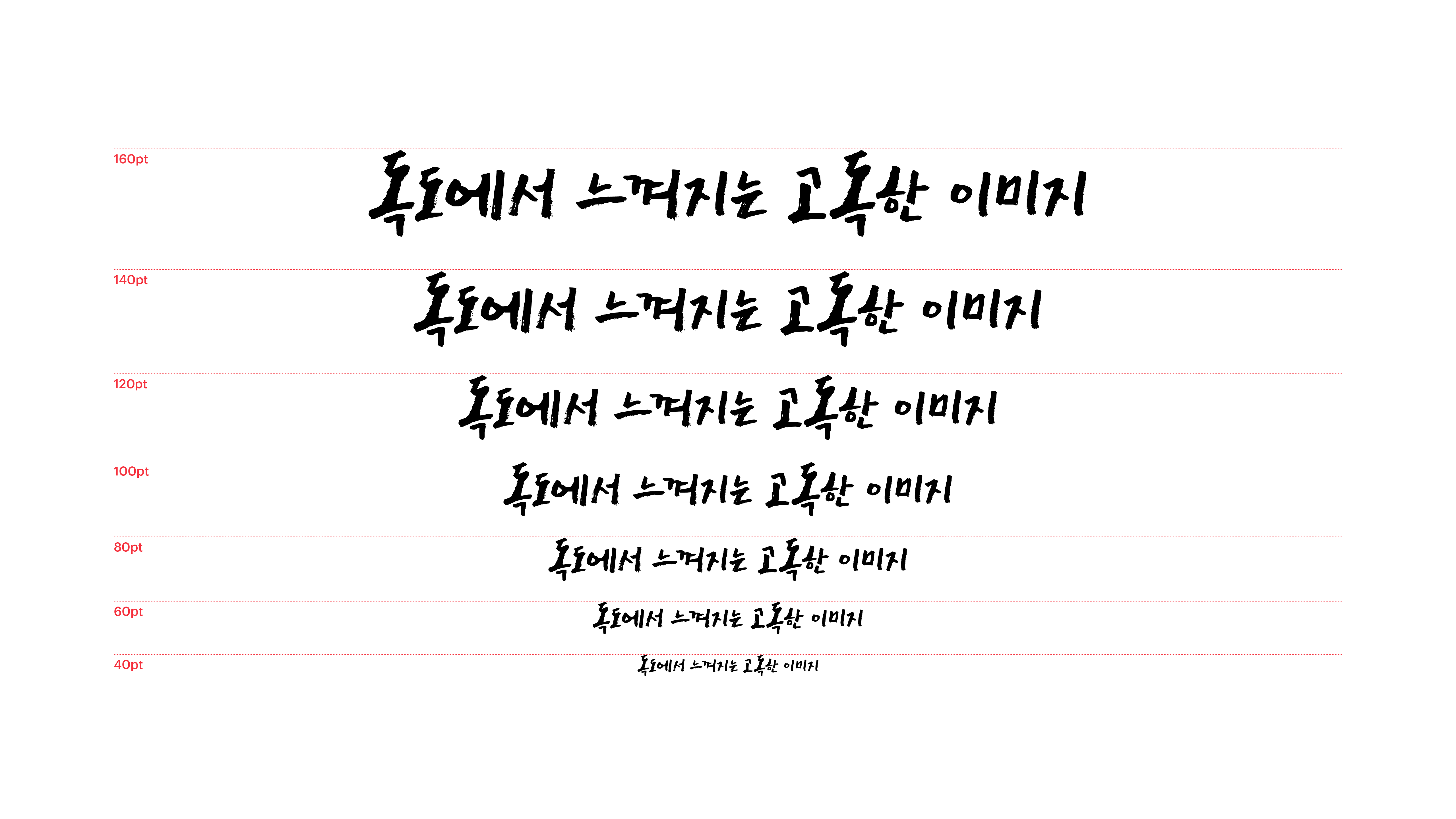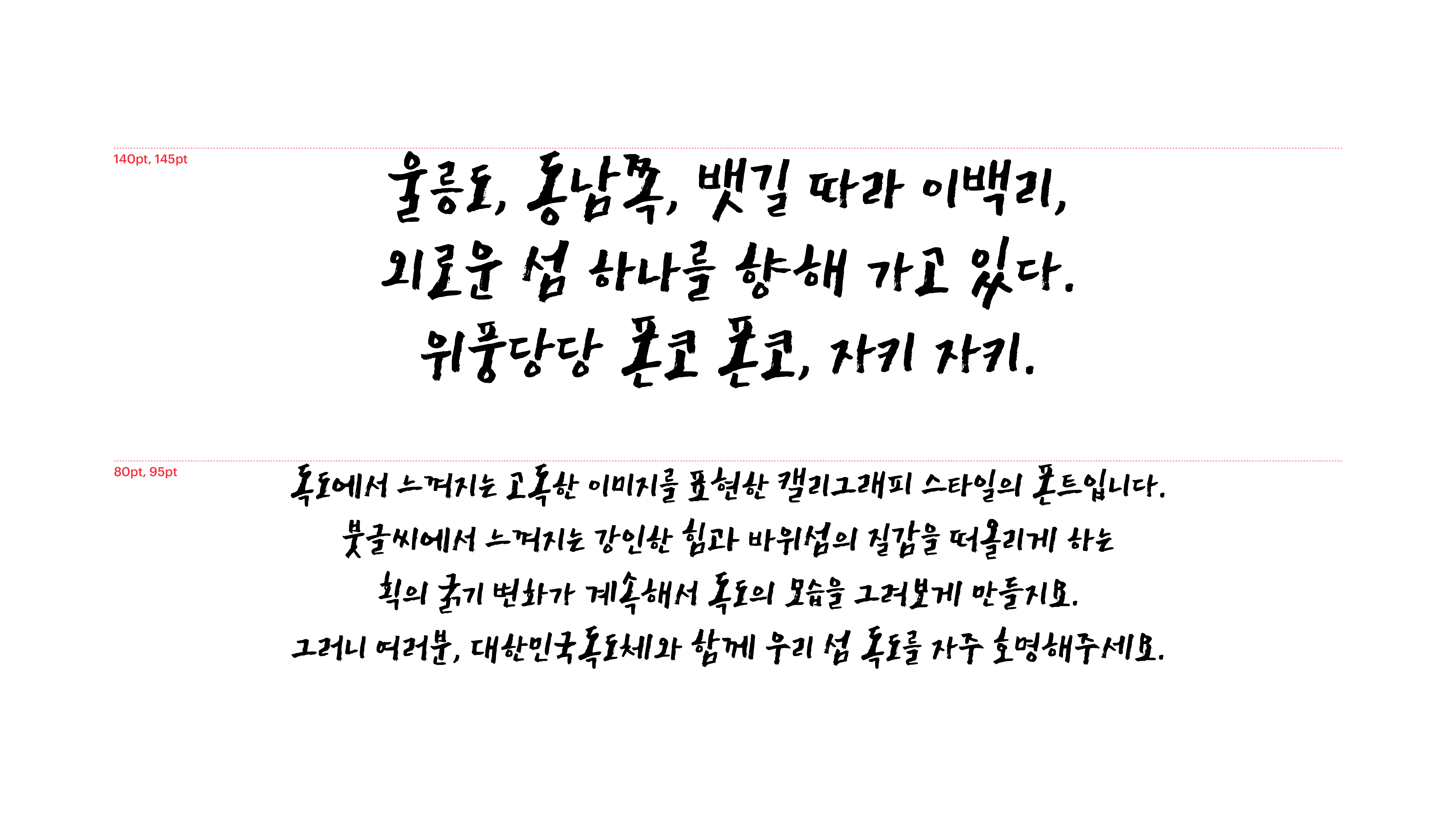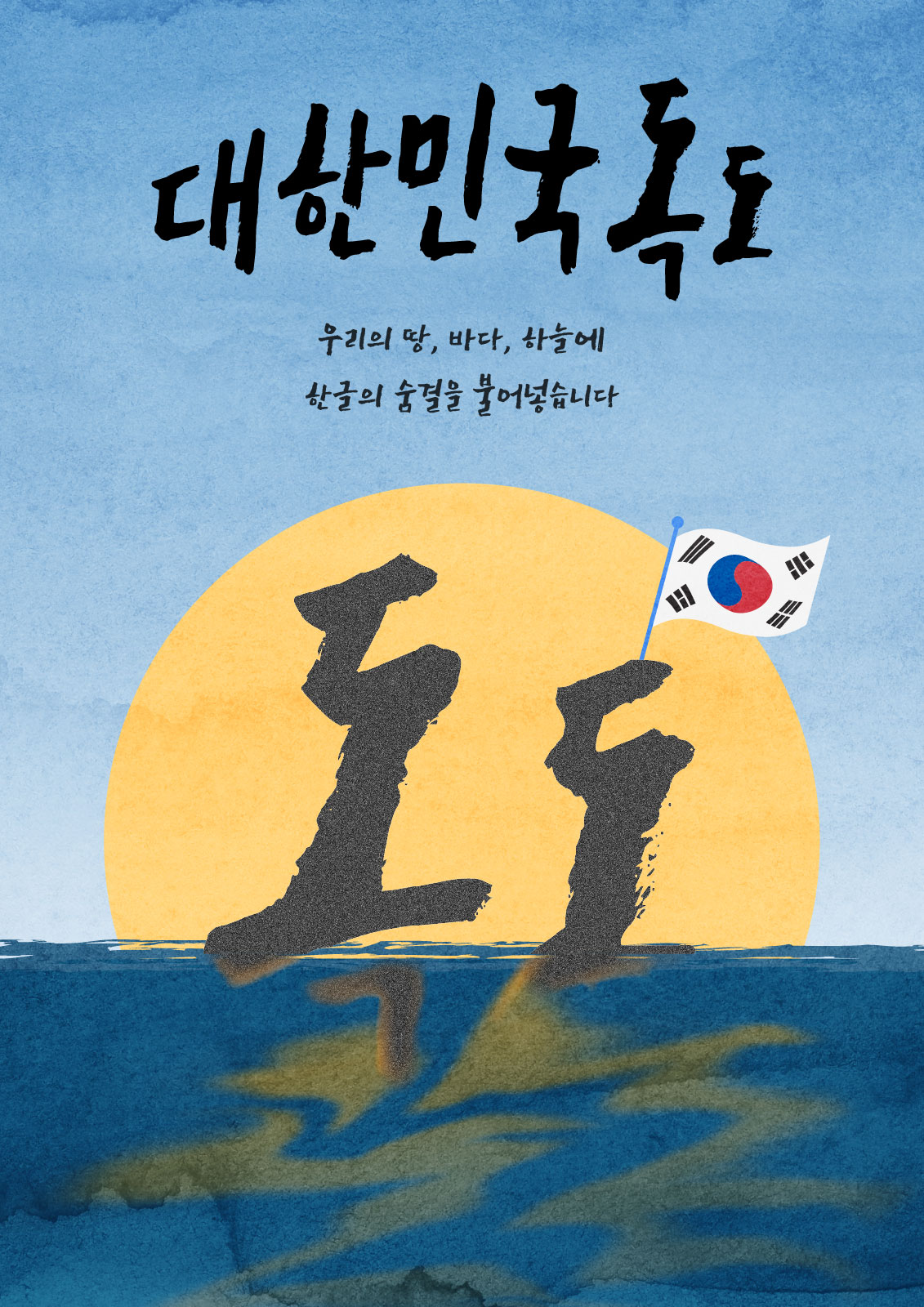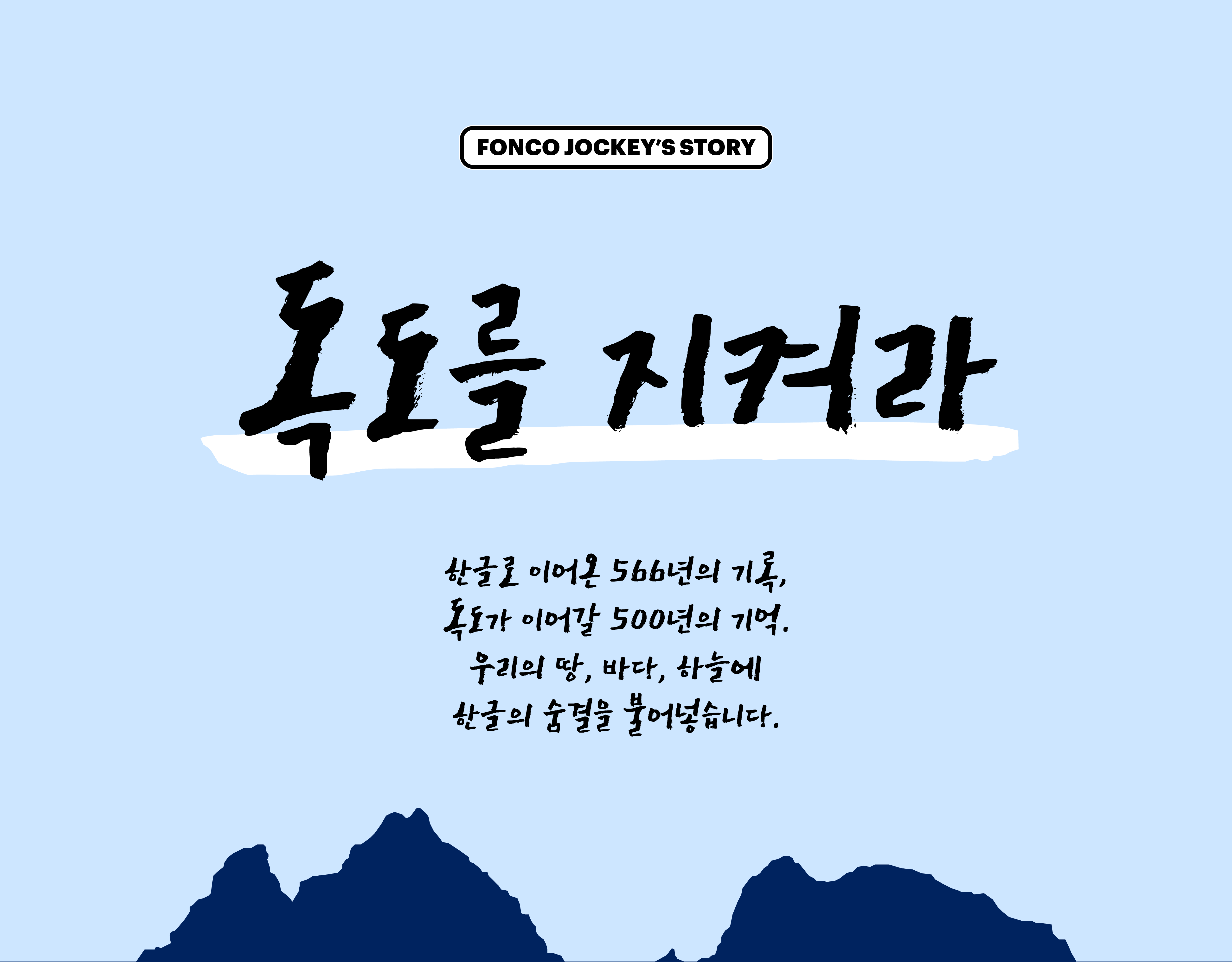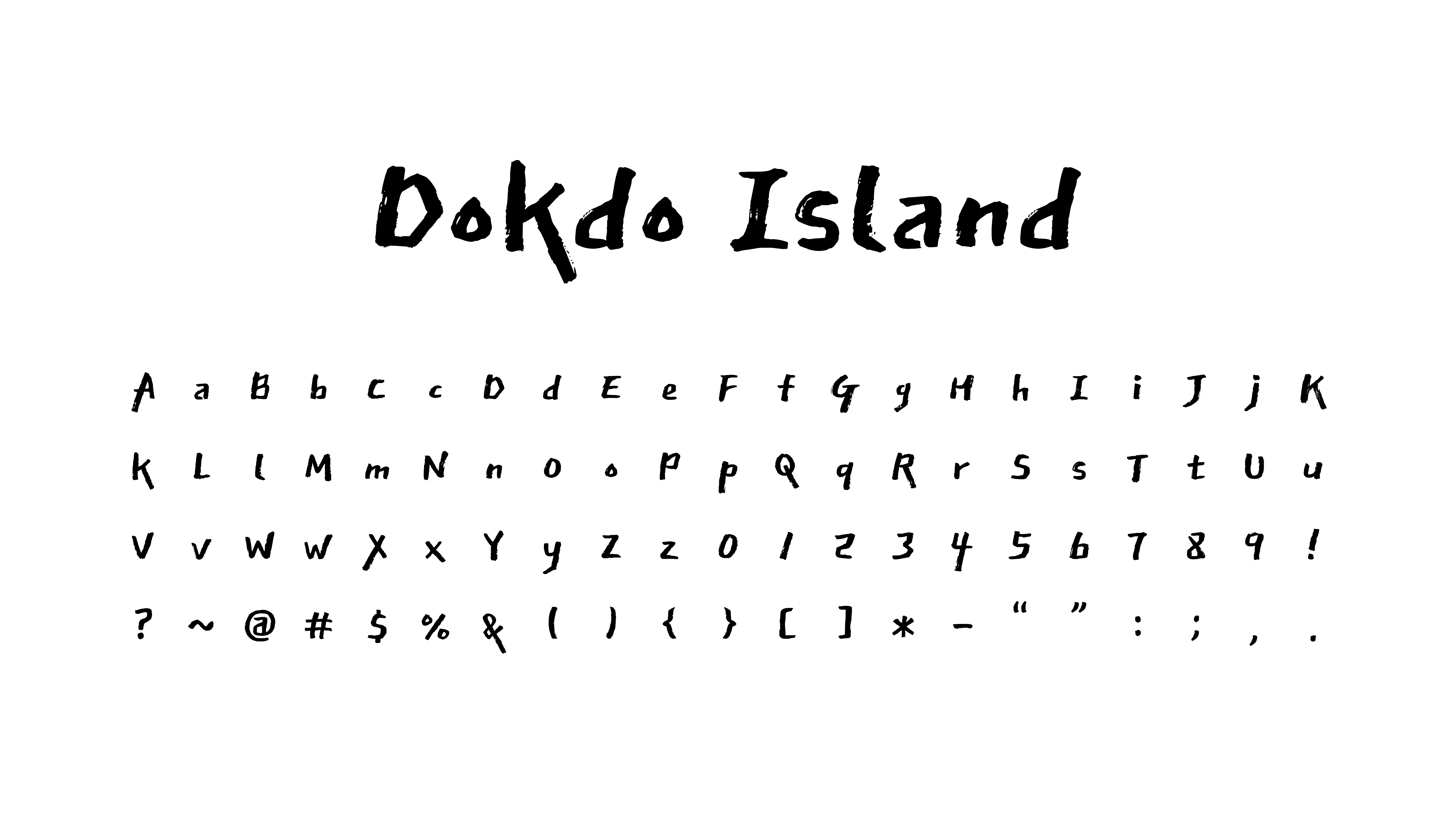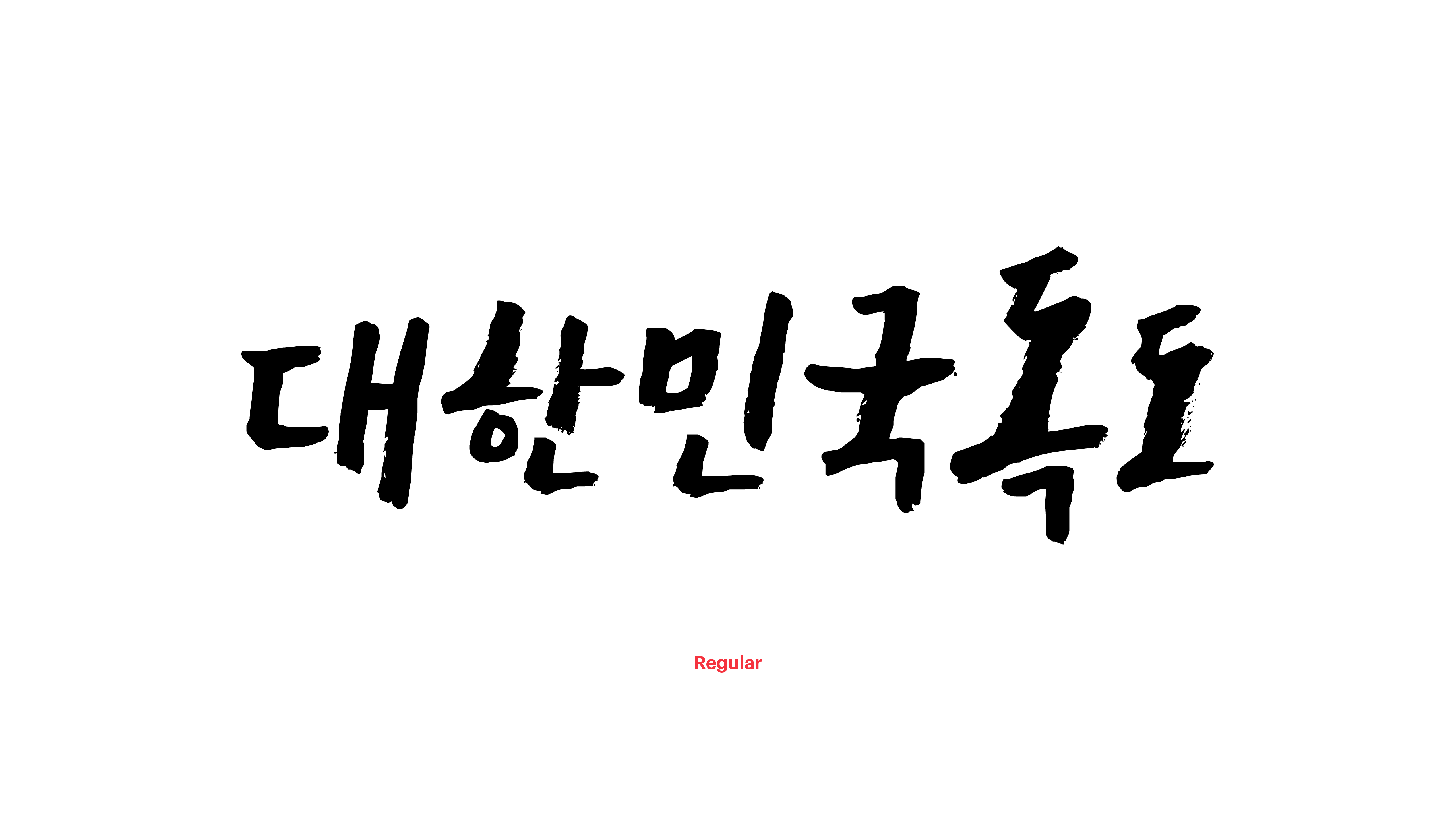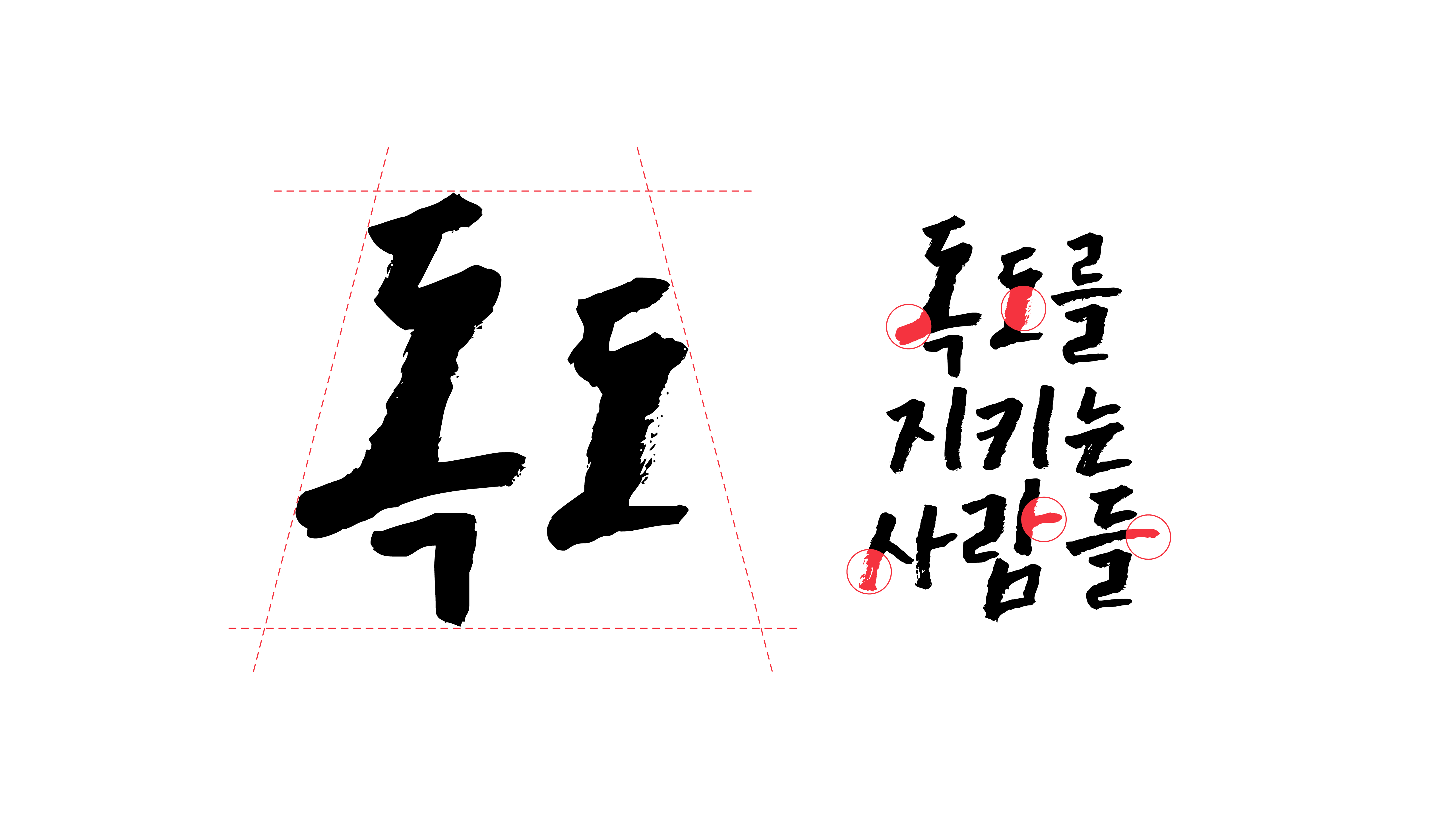
대한민국독도
Yoon 대한민국독도
독도에서 느껴지는 고독한 이미지를 표현한 캘리그래피 스타일의 폰트입니다. 붓글씨에서 느껴지는 강인한 힘과 바위섬의 질감을 떠올리게 하는 획의 굵기 변화가 계속해서 독도의 모습을 그려보게 만들지요. 그러니 여러분, 대한민국독도체와 함께 우리 섬 독도를 자주 호명해주세요.